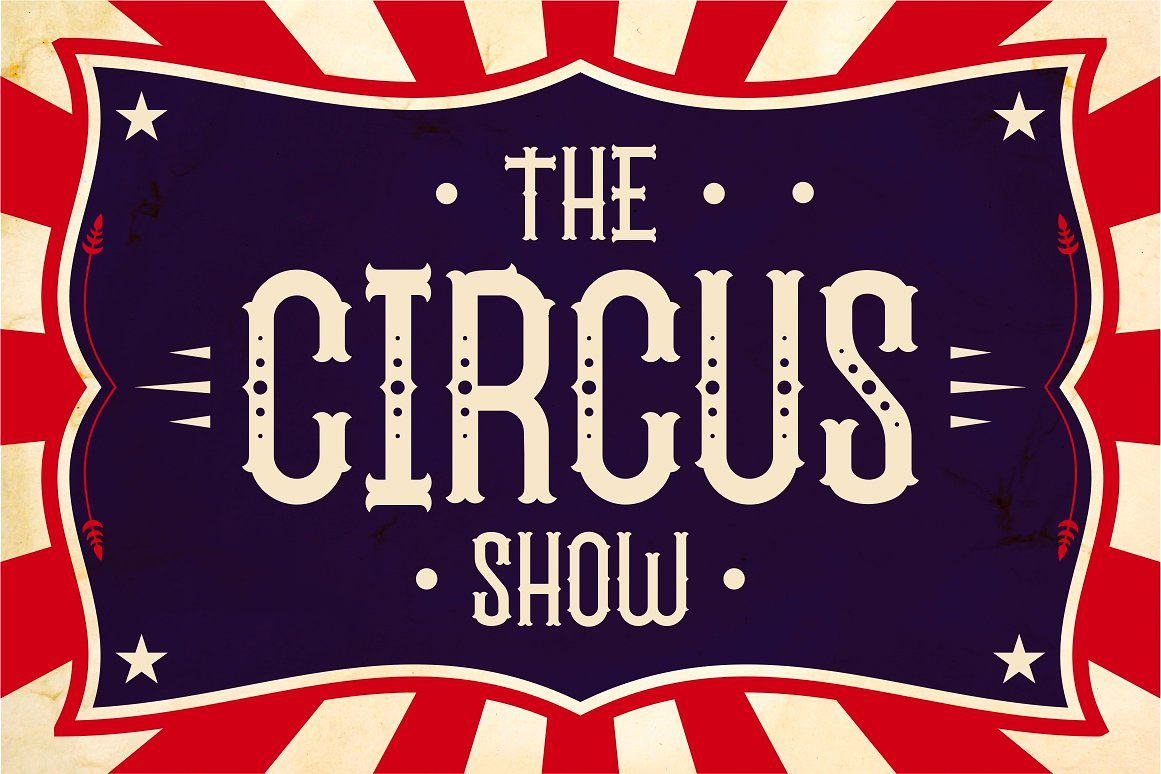
Font Circus là một bộ font việt hóa được thiết kế để bắt lấy tinh thần rực rỡ và náo nhiệt của mùa hè cùng với không khí hấp dẫn của rạp xiếc. Đây là một lựa chọn tuyệt vời cho các dự án thiết kế liên quan đến sự kiện, lễ hội, hoặc các hoạt động giải trí dành cho mọi lứa tuổi . Với những đường nét mạnh mẽ và phóng khoáng, Circus mang đến cảm giác vui tươi, phấn khởi, làm nổi bật nội dung trong một bối cảnh sôi động và vui vẻ.